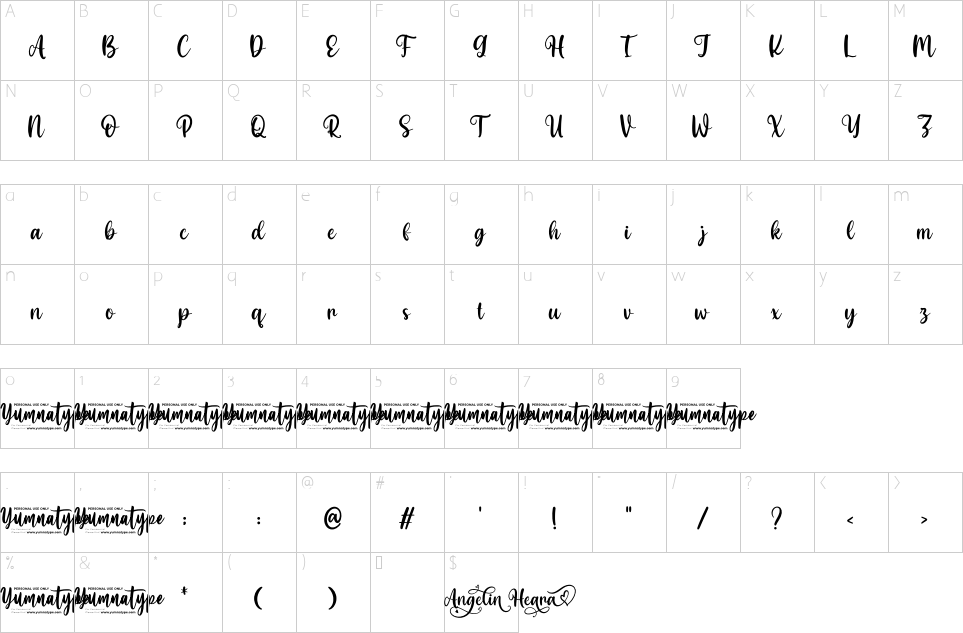
Angelin Heart Font – Download Grátis
Descubra a delicadeza e a elegância de ‘Angelin Heart’, uma fonte gráfica dedicada aos apaixonados. Desenvolvida pela Yumna Type, esta fonte oferece um toque suave e arredondado, ideal para gráficos que expressam sentimentos e emoções. ‘Angelin Heart’ é perfeita para criar mensagens amorosas, logotipos relacionados à paixão e qualquer outro tipo de design que exija um toque delicado e romântico. Sua simplicidade e elegância a tornam uma escolha perfeita para qualquer designer gráfico que procura uma fonte suave e amigável para seus projetos. Com sua facilidade de uso em ambientes Windows e Mac, ‘Angelin Heart’ é uma fonte que vale a pena conhecer e usar. Desde o seu primeiro uso, a fonte já foi baixada 4.387 vezes, uma indicação da sua popularidade e qualidade.